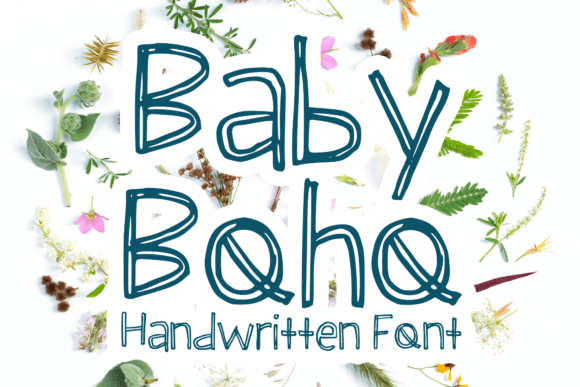
Baby Boho
Ulasan Lengkap Baby Boho – Font Handwritten Boho untuk Anak
Se você está procurando uma tipografia que traga vibes descontraídas e energia hippie para projetos infantis, o Baby Boho é a escolha ideal. Desenvolvido especialmente para crianças, esse font manuscrito combina estilo boêmio com legibilidade, tornando‑se perfeito para camisetas, livros infantis, cartões de felicitações, adesivos e pôsteres.
Por que escolher o Baby Boho?
- Estilo único e alegre – Cada letra tem um traço orgânico que lembra desenhos feitos à mão, ideal para transmitir um toque casual e divertido.
- Versatilidade criativa – Funciona perfeitamente em t‑shirts, capas de livros, convites de aniversário, etiquetas de produtos e muito mais.
- Leitura fácil – Apesar do visual artesanal, as formas são claras e bem espaçadas, garantindo que o texto seja compreensível para crianças e adultos.
Como usar o Baby Boho no seu projeto
- **Camisetas e roupas infantis** – Combine o font com cores pastel ou tons terrosos para reforçar o clima boho‑chic.
- **Livros e histórias para crianças** – Use o Baby Boho nos títulos e nas páginas de destaque para dar personalidade às ilustrações.
- **Cartões de aniversário e felicitações** – Crie mensagens calorosas que transmitam “good vibes” instantaneamente.
- **Adesivos e pôsteres decorativos** – Aplique o font em frases curtas como “Stay Wild” ou “Dream Big” para paredes de quartos infantis.
Benefícios de escolher um font temático como o Baby Boho
Um font temático ajuda a criar identidade visual consistente e a conectar emocionalmente com o público‑alvo. No caso do Baby Boho, a atmosfera hippie e descontraída combina com a curiosidade natural das crianças, estimulando criatividade e positividade.
Se o seu objetivo é transmitir boho vibes em projetos para crianças, o Baby Boho oferece a combinação perfeita de estilo artesanal, legibilidade e flexibilidade de uso. Experimente agora e sinta a energia positiva que só um font manuscrito pode proporcionar!